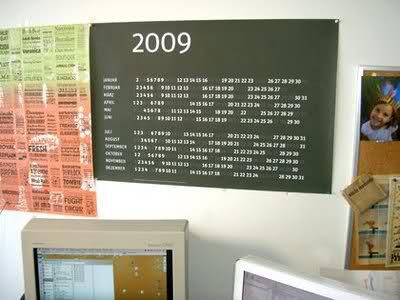
Das ganze Jahr im Flattersatz – Kalender 2009
Sind für das Plakat vielleicht noch andere Farben geplant? Dieses grünliche Türkis finde ich nicht so speziell.
Der (Gewinn-)Kalender ist eingetroffen – danke, Christian – und macht sich sehr gut, wie ich finde:
Habe ein wenig jonglieren müssen, da auch bei mir wenig freier Wandplatz vorhanden ist. Aber jetzt habe ich ihn gut im Blick und er sieht fantastisch aus. Herzliche Gratulation für die Idee und Ausführung, Christian.
hey, schöne Bilder. Freut mich, dass du noch ein Plätzchen für den nicht gerade kleinen Kalender gefunden hast.
Übrigens, wie schon oft heute passiert: Gerade kam eine Kollegin rein und sagte: »Oh, cooler, neuer Kalender …«